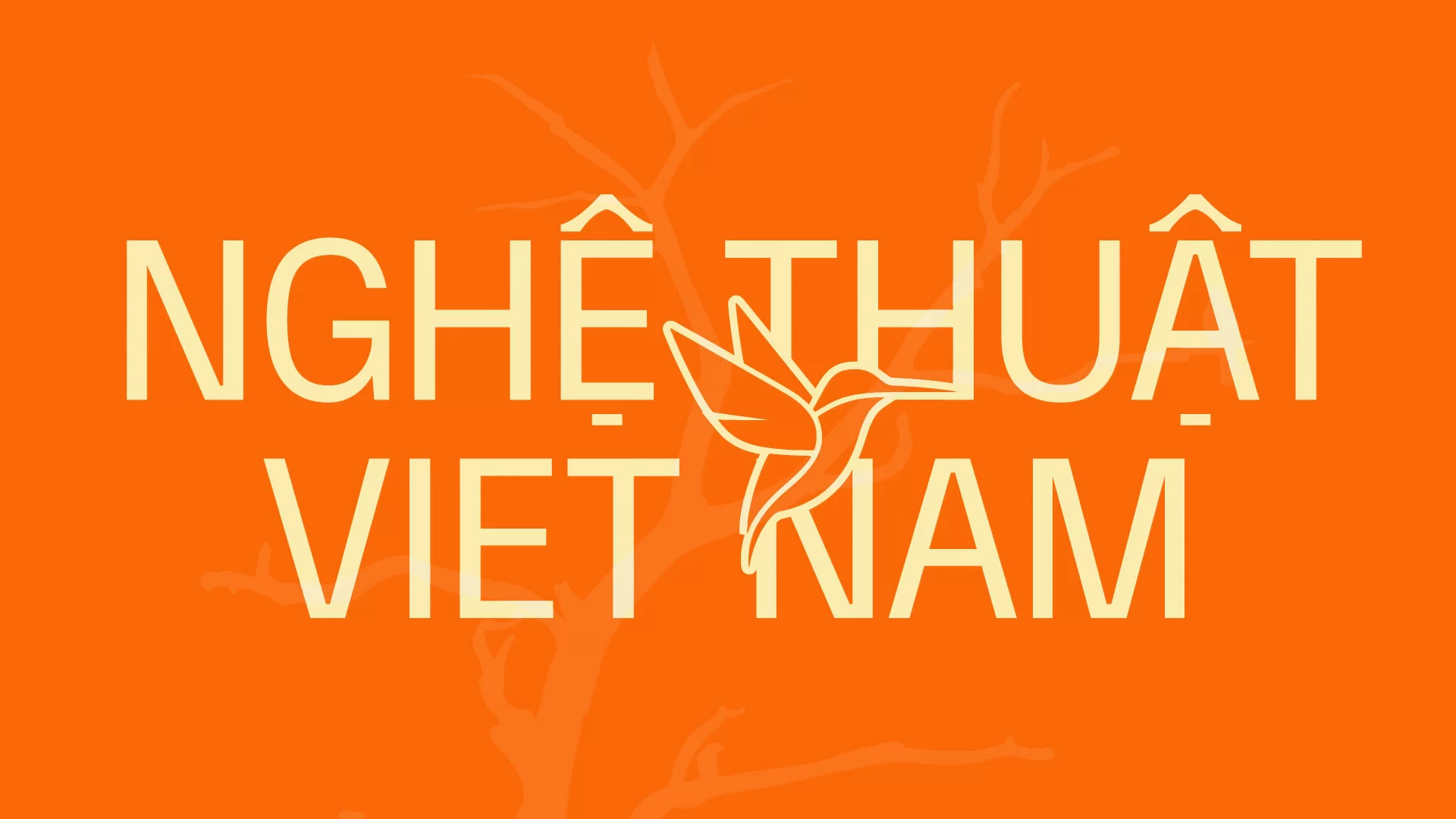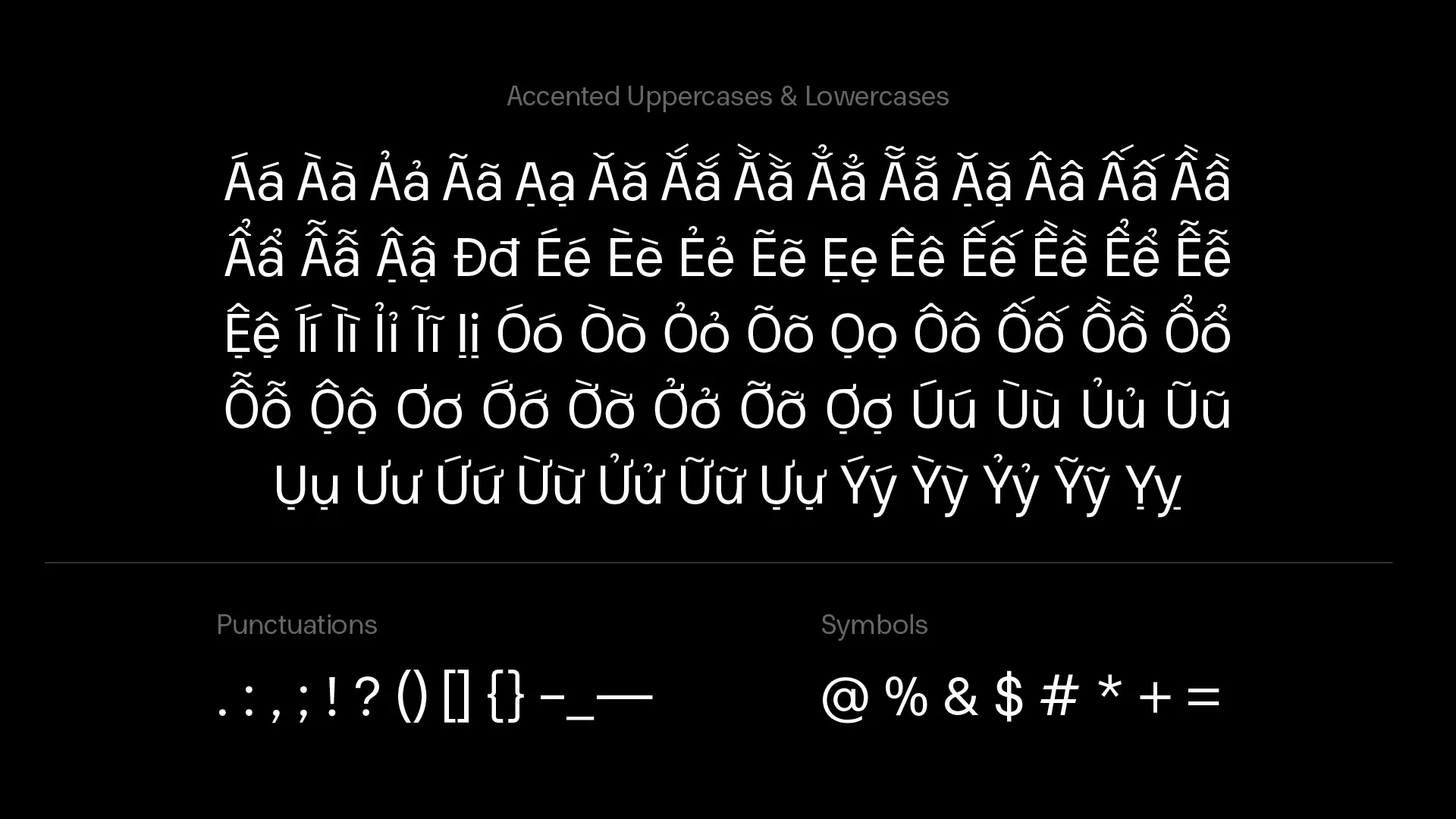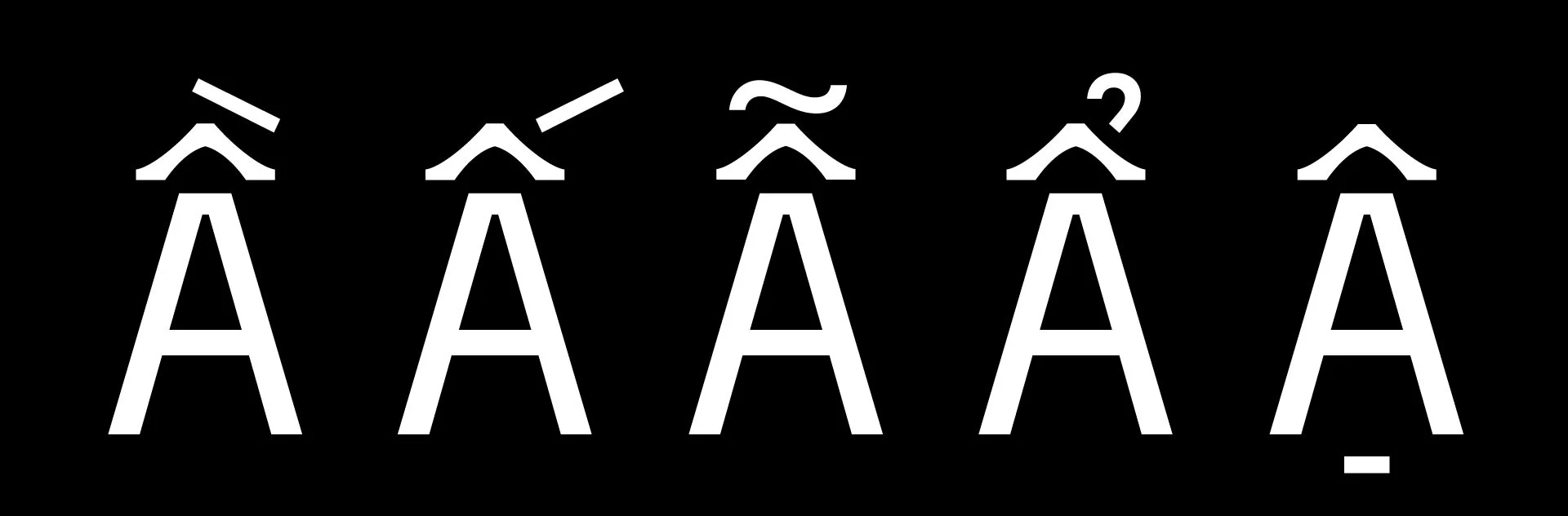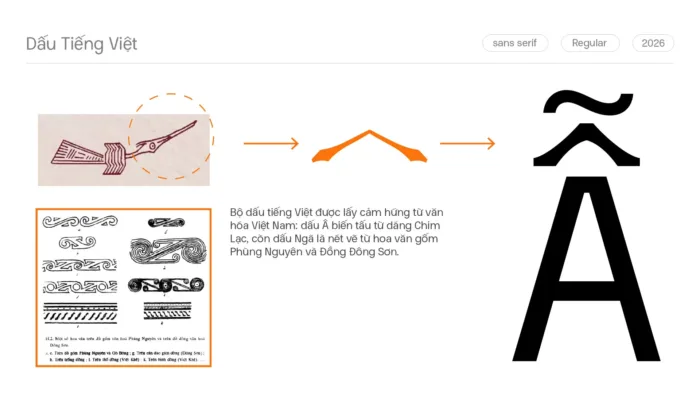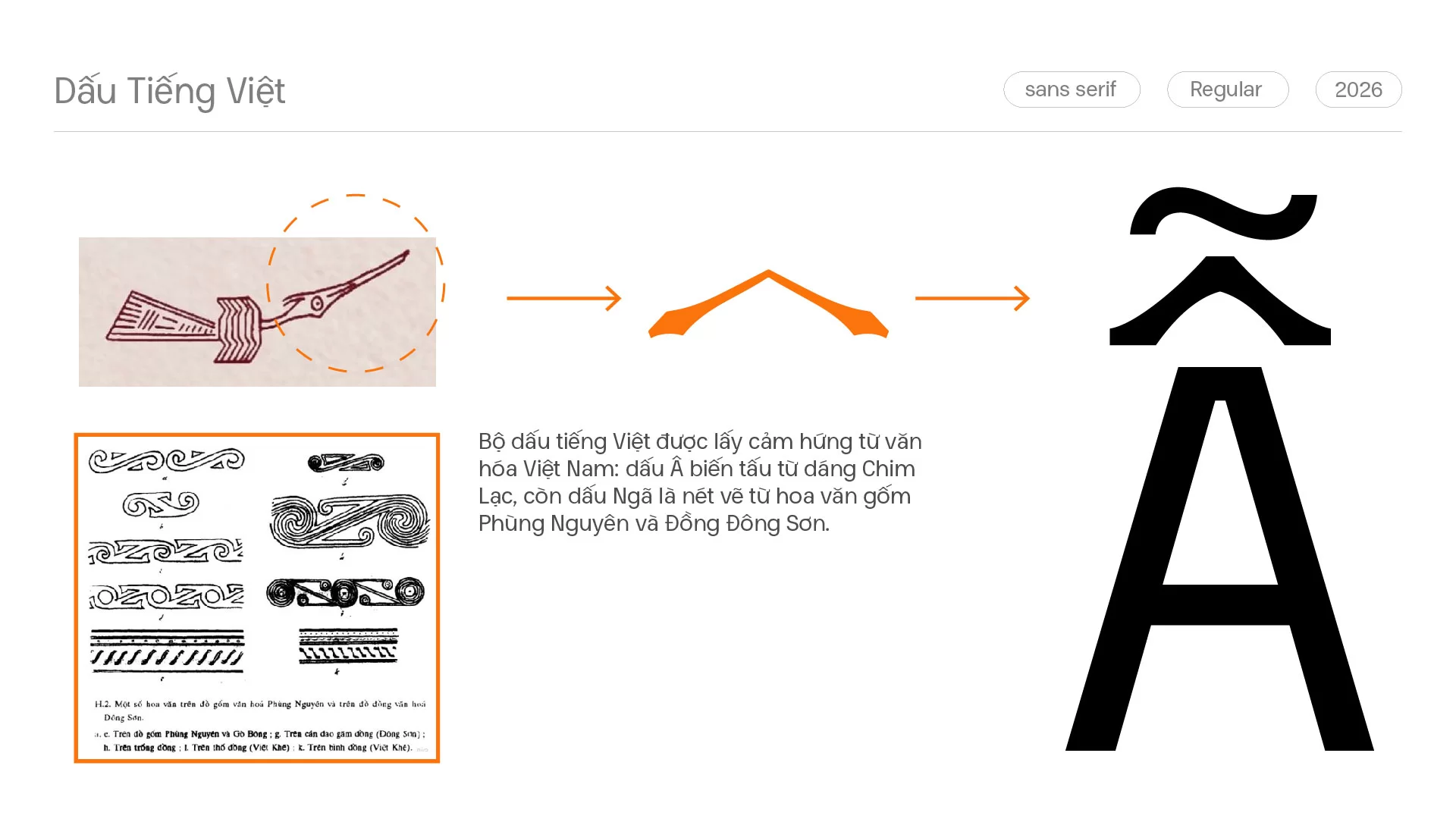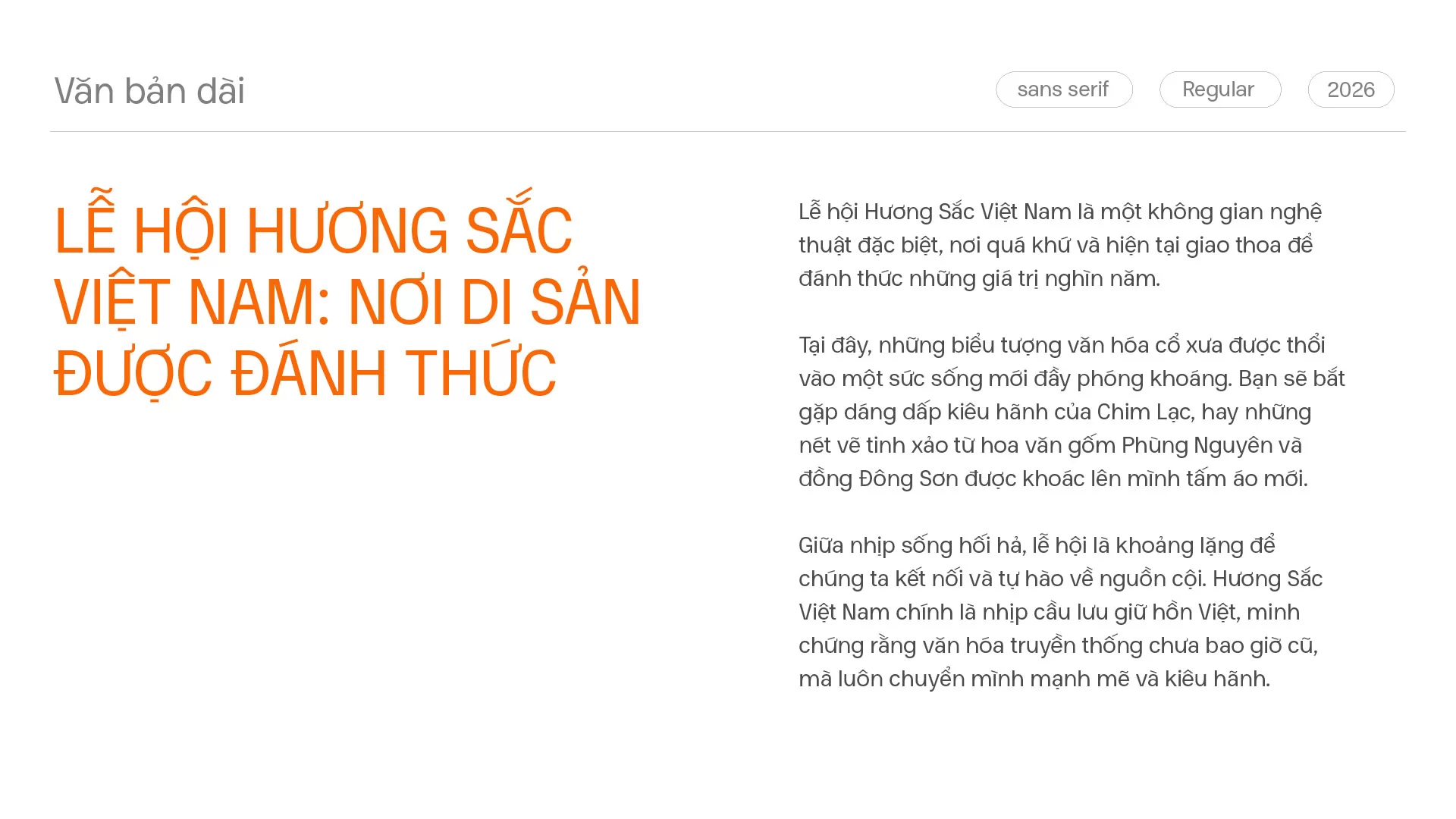
Young Lạc – Font Tiếng Việt sans-serif từ cảm hứng chim lạc
Young Lạc là phiên bản cải tiến từ font gốc Young Type, giữ trọn cấu trúc neo-grotesque hiện đại, tối giản nhưng mang đậm bản sắc Việt qua bộ dấu diacritics.